输入一个词,挑一个样式,下载 PNG。就这么简单,大约十秒钟。
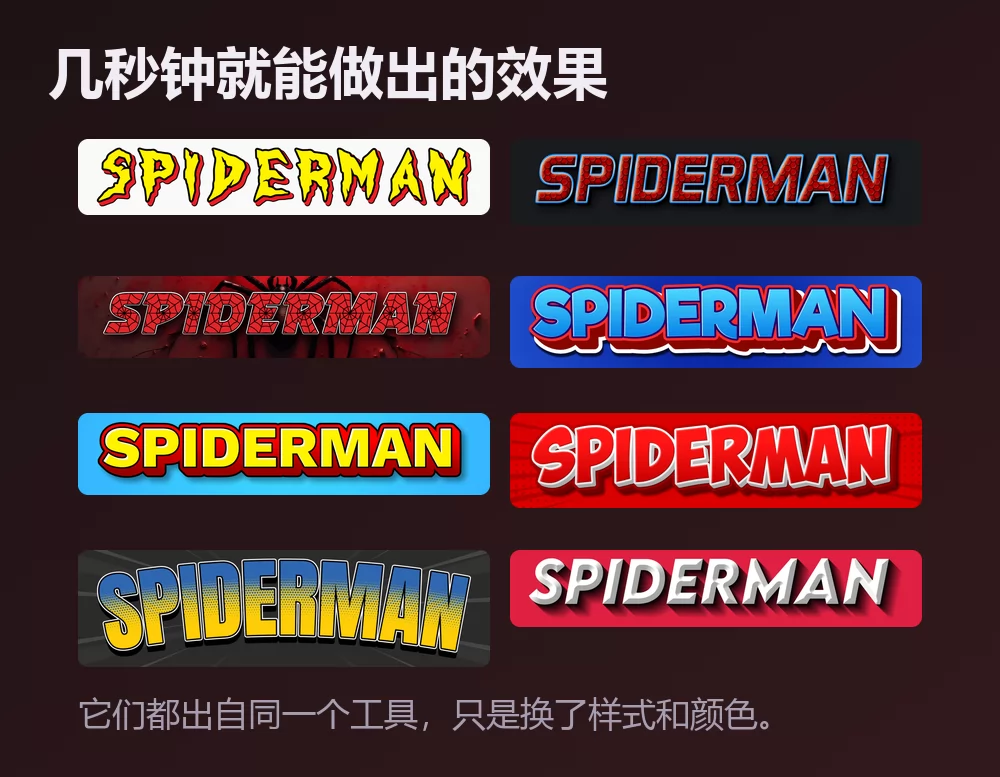
它们都出自同一个蜘蛛侠字体生成器,只是在列表里换了样式。无需安装,无需账号。
怎样做蜘蛛侠文字
第一步:输入文字
打开生成器,把示例文字换成你自己的:名字、派对标题、频道名称、视频标题。字母会随着输入实时重绘。
第二步:挑一个样式
最经典的是锯齿状黄色字样配粗红描边,直接来自漫画封面。「样式」标签页可以分别改填充、描边和阴影:字形保留,配色可以带去别处。
第三步:选好尺寸
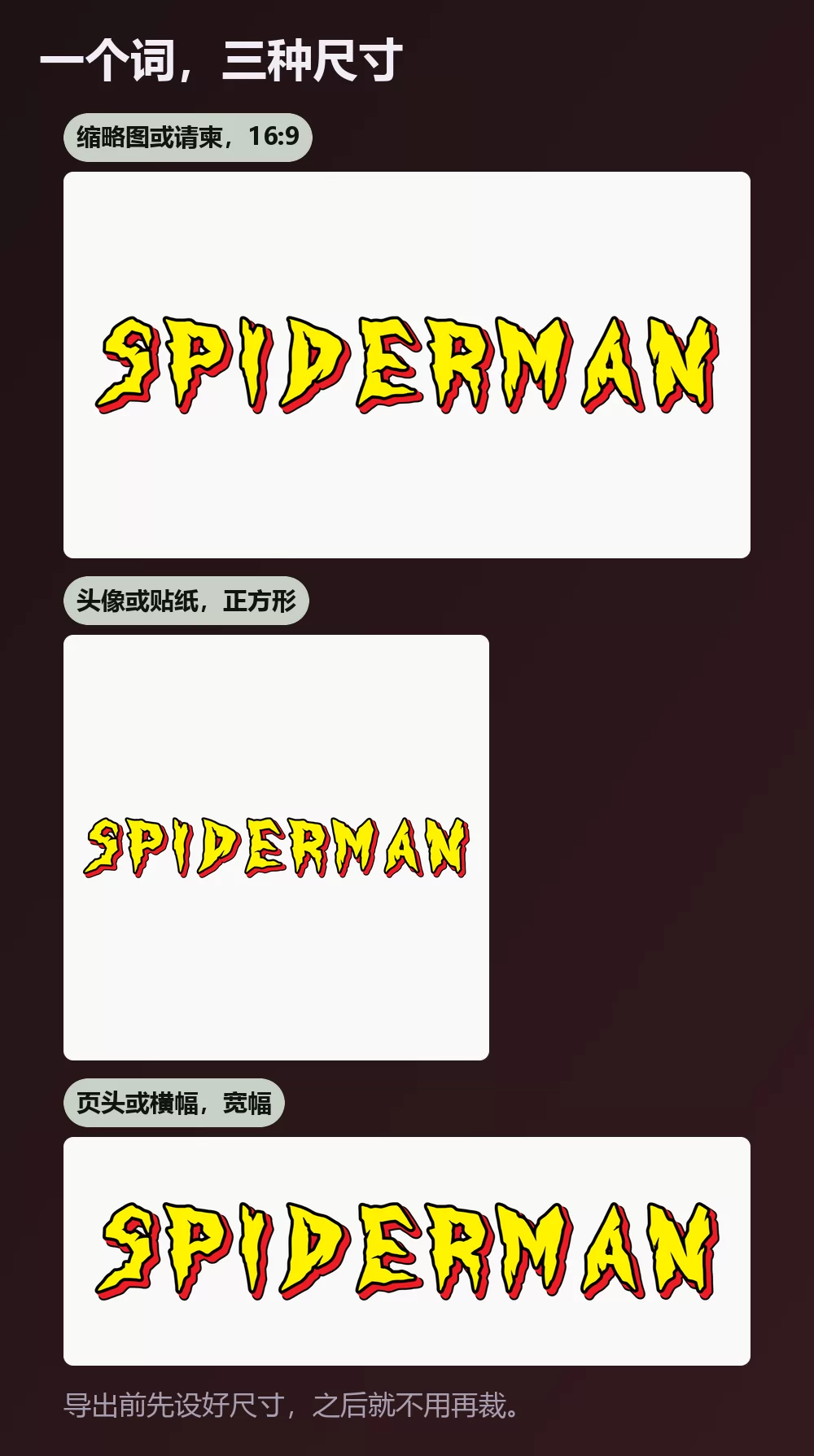
导出前先设好尺寸,之后就不用再裁。视频缩略图或请柬用 16:9,头像或贴纸用正方形,频道页头用宽条。
第四步:下载
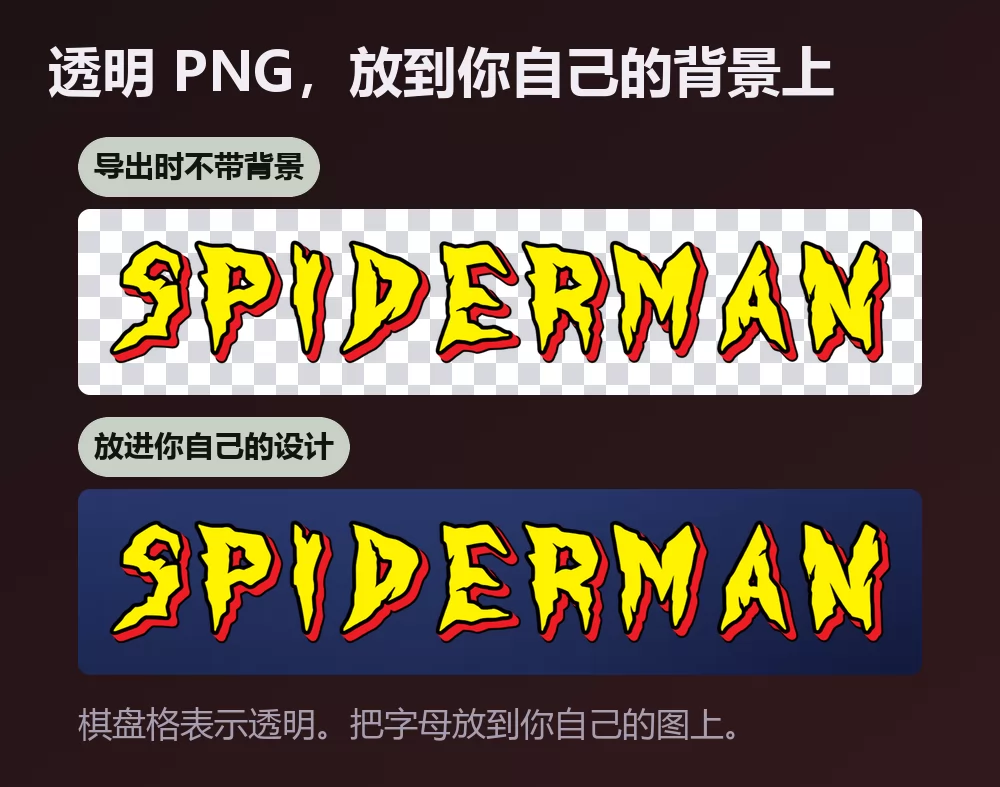
如果打算把字母放到自己的图上,就在「下载」标签页里选透明 PNG。这个选项多数人会漏掉,而它恰恰最关键:你自己的背景,标题在上,周围没有白框。
名字一长,宽度很快就满了
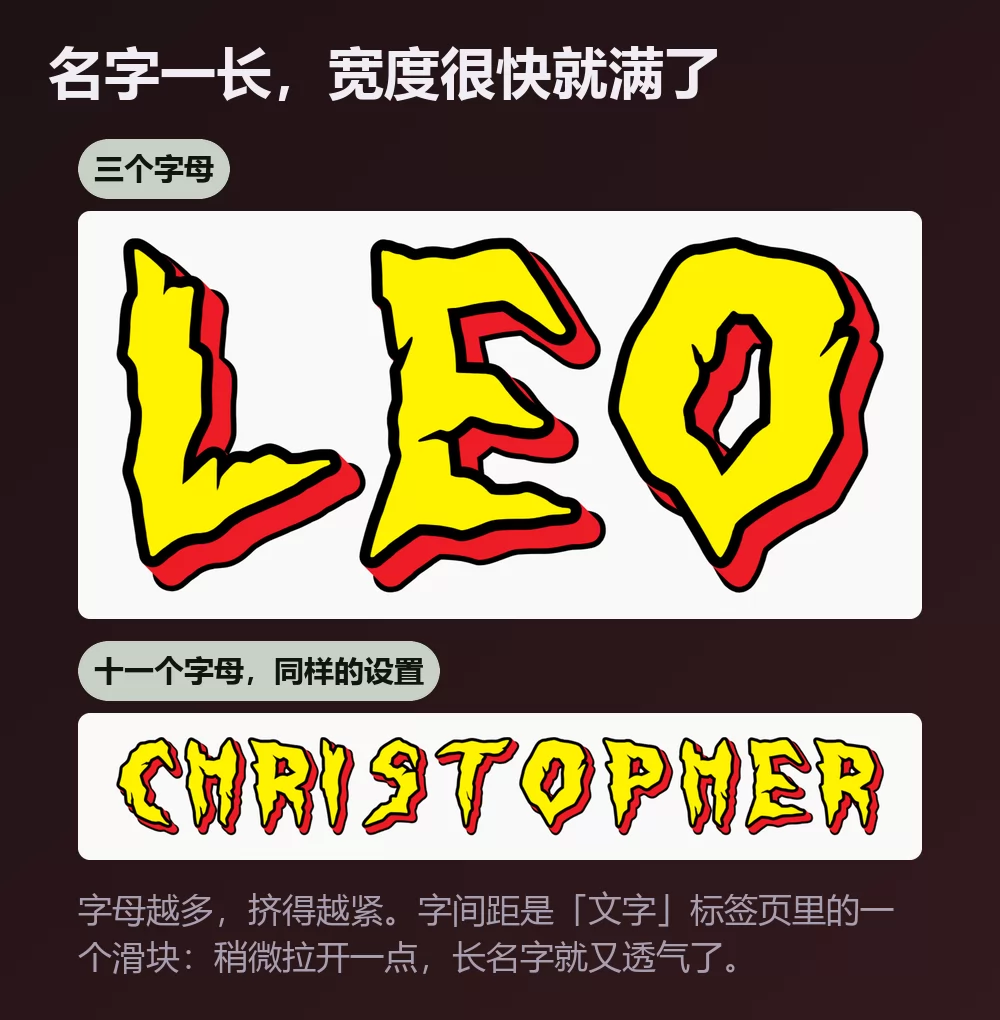
字母越多,挤得越紧。字间距是「文字」标签页里的一个滑块:稍微拉开一点,长名字就不再显得局促。同一个标签页里还有缩放、行距、弯曲和旋转。
漫画的样子,还是电影的样子
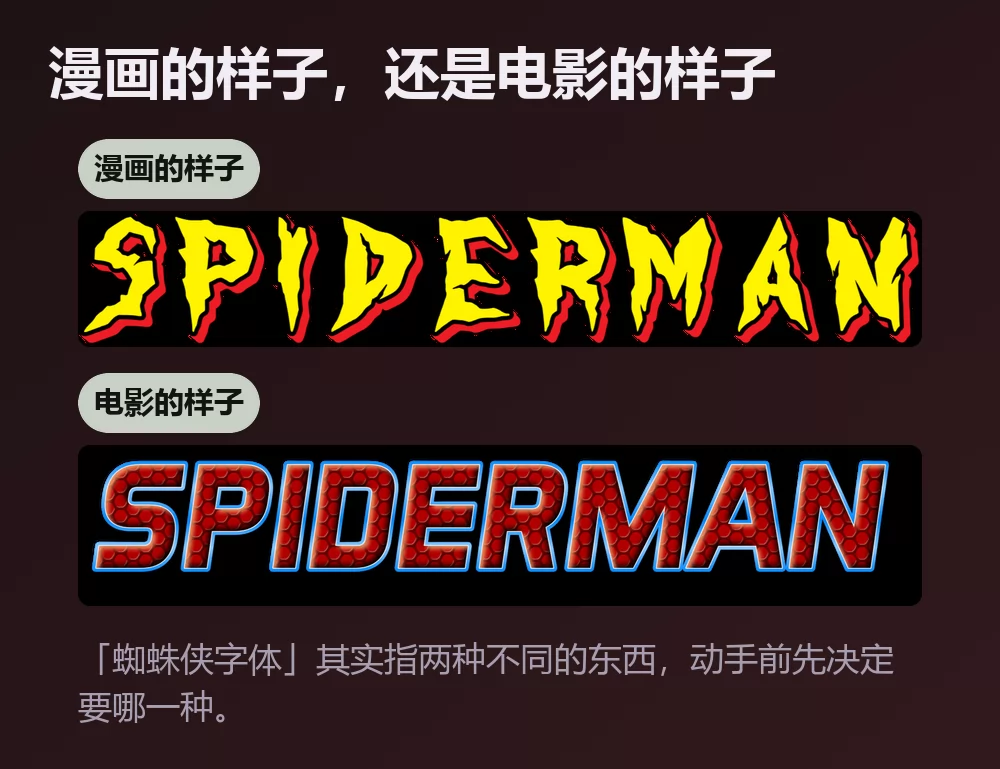
「蜘蛛侠字体」其实指两种不同的东西,最好先弄清自己要哪一种。
漫画的样子是带粗红描边的锯齿黄色字样,几十年封面上的那一种。多数人想到的是它,上面的生成器给的也是它。
电影的样子更光滑、更暗:字身带着红色蛛网质感,边缘为蓝色,更接近现代海报而不是漫画。
蛛网这一点值得弄明白,因为它不是字体给的。它是覆盖在字母上的一层质感。你想装哪款仿制字体都行,还是得不到它:它来自叠加在上面的效果,而这正是生成器一步就完成的事。
想装字体的话,该装哪一款
怎样在 Canva 里做蜘蛛侠文字
Canva 的字体库里没有蜘蛛侠字体,免费版也不能自行安装。把字样做成透明 PNG 再上传:它可以直接放进 Canva 设计稿,而且保持清晰。
如果你常在 Canva 里工作,也可以在 Canva 里直接用 TextStudio 效果,省掉上传这一步。
怎样在 Photoshop 里做蜘蛛侠文字
装一款复刻字体,打好字,再用图层样式把处理效果搭出来:
- 颜色叠加,用明亮的黄色。
- 描边,设为外部、饱和的红色、加粗。
- 投影,收紧且偏暗。
- 若要电影的样子,则改用图案叠加加蛛网纹理,剪贴到文字上,再加一圈细蓝描边。
蛛网是最费工的一步。蛛网图案必须顺着字母走,而不是留在后面,这意味着要把纹理图层剪贴到文字上,再一点点挪动,直到丝线落在眼睛预期的位置。
怎样在 Word 里做蜘蛛侠文字
装好字体,打好字,再用文字效果做描边和阴影。Word 无法用纹理填充文字,所以蛛网在那里做不到。凡是要打印或发布的东西,导出的 PNG 都会更好看。
在手机上
无论 iOS 还是 Android,都没法装一款字体再在多数应用里使用。生成器在手机浏览器里就能跑:在手机上做好 PNG,存进相册,再在你原本要用的应用里添加。
常见问题
蜘蛛侠标志用的是什么字体? 是手绘字样,而不是已发布的字体。所有能下载的都是粉丝复刻。
哪款免费字体最像蜘蛛侠? 电影片名用 Homoarakhn,漫画字样用 mightyspidey。只有 Homoarakhn 标注为可免费商用。
怎样让字母带上蛛网质感? 靠字体做不到。那是覆盖在字母上的质感:要么用生成器里自带该效果的样式,要么在 Photoshop 里把蛛网图案剪贴到文字上。
怎样得到透明背景? 在「下载」标签页里选透明 PNG,再把字母放到你自己的图上。
为什么我做出来的字跟海报完全不像? 多半是蛛网和描边的问题,而不是字形。这两项比选字体更起作用。